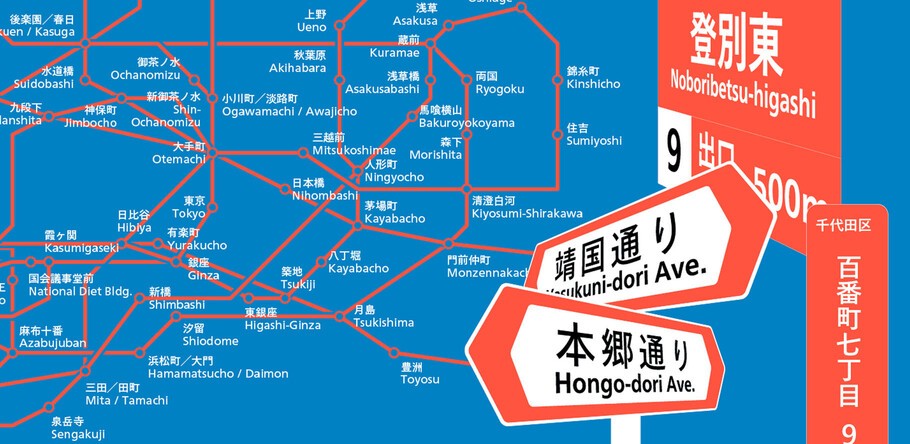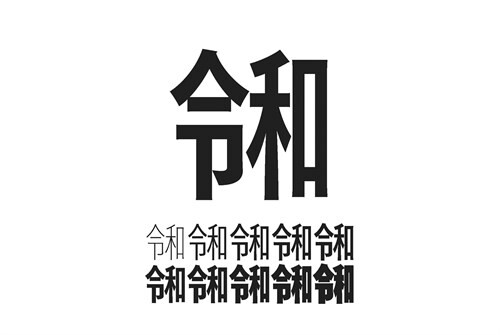
Monotype 向 Tazugane 系列字体中添加了 “令和” 合字字形。
他们设计了这一新字形,来体现令和的希望——以日本悠久的历史、丰富的文化和美丽的自然为基础,推动国家发展。
日本政府最近公布,新天皇即位后的时代将被称作 “令和”。新元号将在 5 月 1 日皇太子德仁即位后正式启用。
令和时代开始的标志,是新年号字形加入了日文书写系统,这意味着日文字体家族必须更新来支持这一新字符。今天,Monotype 为其广受欢迎的 Tazugane Gothic 和 Tazugane Info 字体推出了新的字形设计,拥有字体授权的品牌和创意专业人士可以立刻使用。
Monotype 的字体总监小林章和字体设计师土井辽太设计了这一新字形,来体现令和的希望——以日本悠久的历史、丰富的文化和美丽的自然为基础,推动国家发展。
对于寻求如何将新年号纳入品牌设计的创意专业人士而言,新字形的设计为他们提供了广泛的交流机会。当前的 Tazugane Gothic 和 Tazugane Info 用户将收到令和合字字形,并编入字体当中;新用户的字体字符集中则会包含这一字形。此外,Monotype 工作室将与其品牌客户密切合作,以确保字形添加到他们的定制字体设计中。
土井辽太.
土井辽太是蒙纳的字体设计师。在日本读大学期间,作为一名设计专业的学生,土井第一次对字体产生了兴趣。在东京艺术大学获得设计学士学位后,他参加了著名的雷丁大学的字体设计硕士课程,研究日文字体与拉丁字体之间的区别。